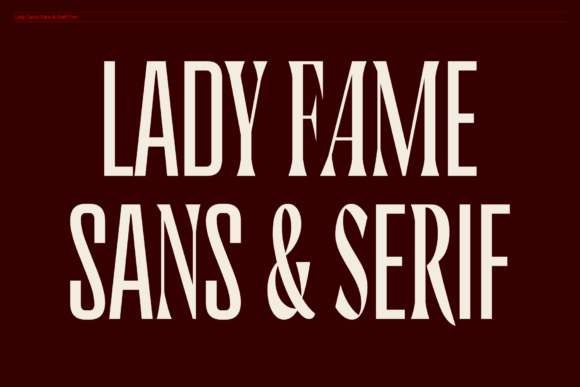
Lady Fame Duo
Znalezienie odpowiednich elementów projektu może być wyzwaniem, ale Lady Fame Duo oferuje wyjątkową kolekcję, która natychmiast ulepszy Twoją pracę.
Precyzyjnie wykonany, Lady Fame Duo zapewnia czyste wektory, płynną typografię i licencję komercyjną dla Twojego spokoju.
Niezależnie od tego, czy tworzysz produkty POD (druk na żądanie), zaproszenia ślubne czy grafiki do mediów społecznościowych, Lady Fame Duo będzie idealnym wyborem.